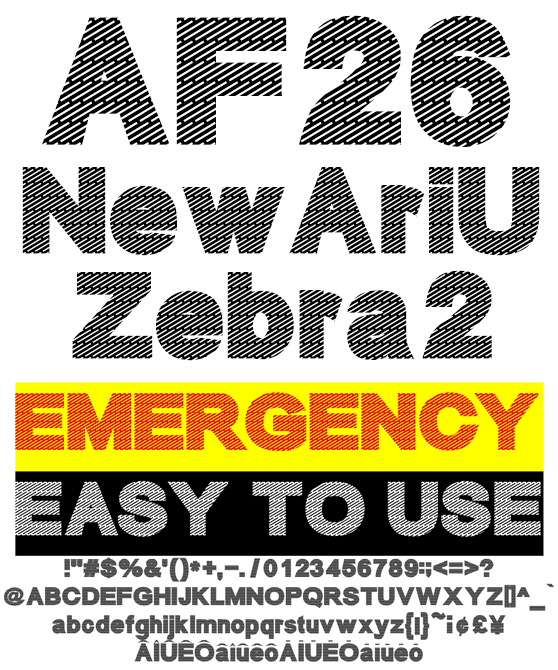
サンセリフ
ゼブラ欧文 AF26NewAriUZebra2
AF26NewAriUZebra2
袋文字に斜線でゼブラ模様を施しました。インパクトを与えたい場所、注意書きの見出し、警告への利用に最適です。大きなサイズでご利用ください。平凡ながら極太デザインは強くメッセージを伝えます。記号類、マクロンやサーカムフレックスなどのダイアクリティカルマーク、訓令式やヘボン式で扱う Ô やŌを収録、人名地名でもお使い頂けます。